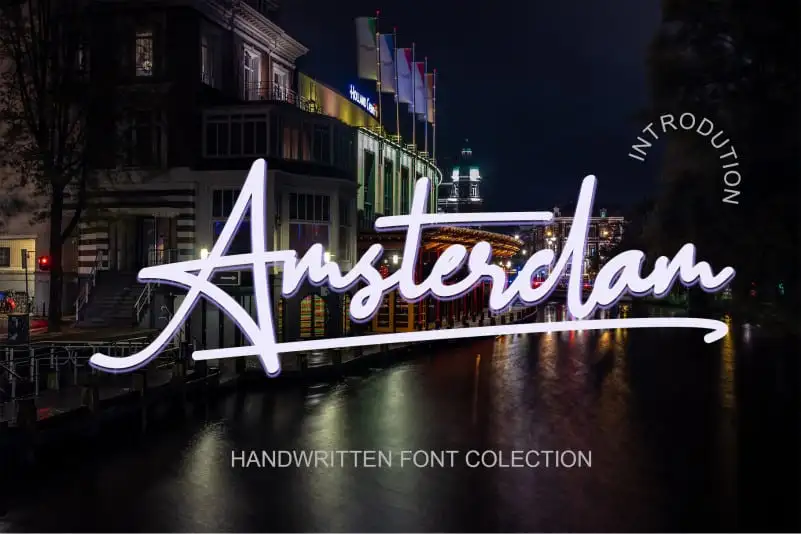
Amsterdam Handwritten Font – Download Grátis
A Amsterdam Handwritten Font é uma deliciosa e eterna escrita a mão que você vai adorar usar. Essa fonte perfeita para criar logotipos atrativos, marcas bem-sucedidas e citações de sucesso. Cada letra possui um toque único e belo, tornando seu design realmente viver! Esta fonte é ideal para aqueles criadores que buscam uma escrita a mão única e autêntica, oferecendo um toque especial à sua obra. Ela não só adicionará um toque de personalidade ao seu trabalho, mas também será capaz de criar uma conexão emocional entre você e o público-alvo, tornando-a uma escolha perfeita para qualquer projeto visual.